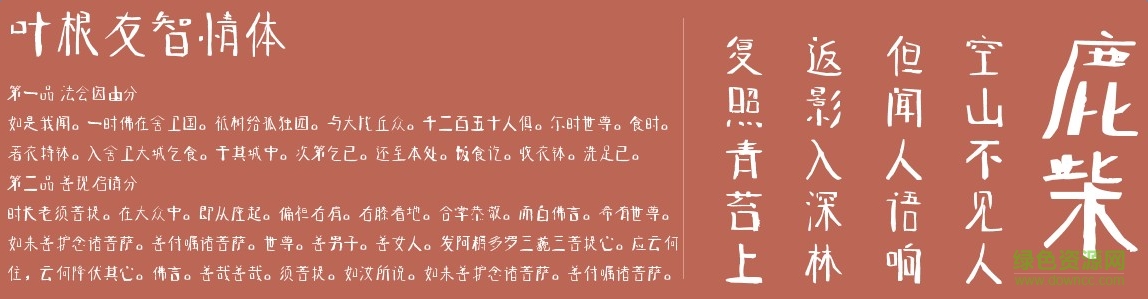
葉根友智情體
葉根友智情字體是一款由知名書法家葉根友創(chuàng)造的字體,適用于廣告設(shè)計(jì)、藝術(shù)、海報設(shè)計(jì)等方面,有需要的朋友們不要錯過了。小編為大家提供免費(fèi)下載地址。歡迎大家來綠色資源網(wǎng)踴躍下載哦!
官方介紹
葉根友智情字體,2016年度最新發(fā)布的字體,是一款柔性的字體,非常靈動有趣,活潑,海報設(shè)計(jì)、藝術(shù)方面可以使用。
小編點(diǎn)評
葉根友智情字體,用途廣泛,是葉根友先生的手寫字體,字體非常靈巧生動,適用于藝術(shù)設(shè)計(jì)等方面。各位字體收藏者可以來看看。